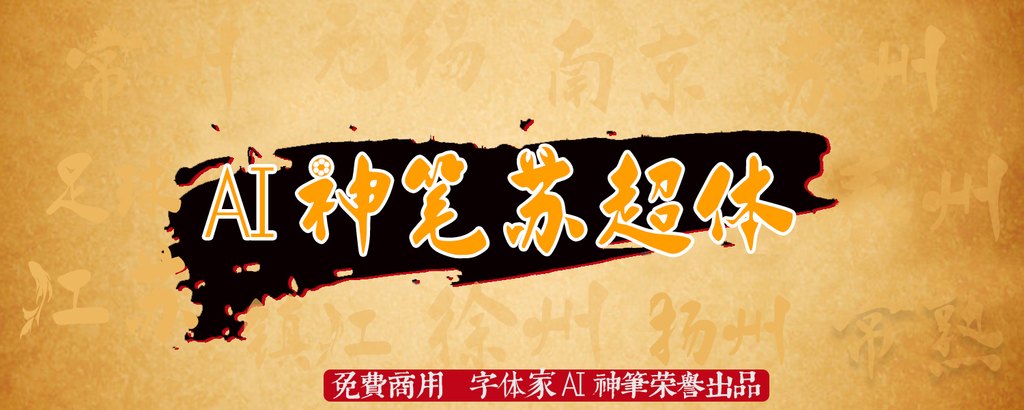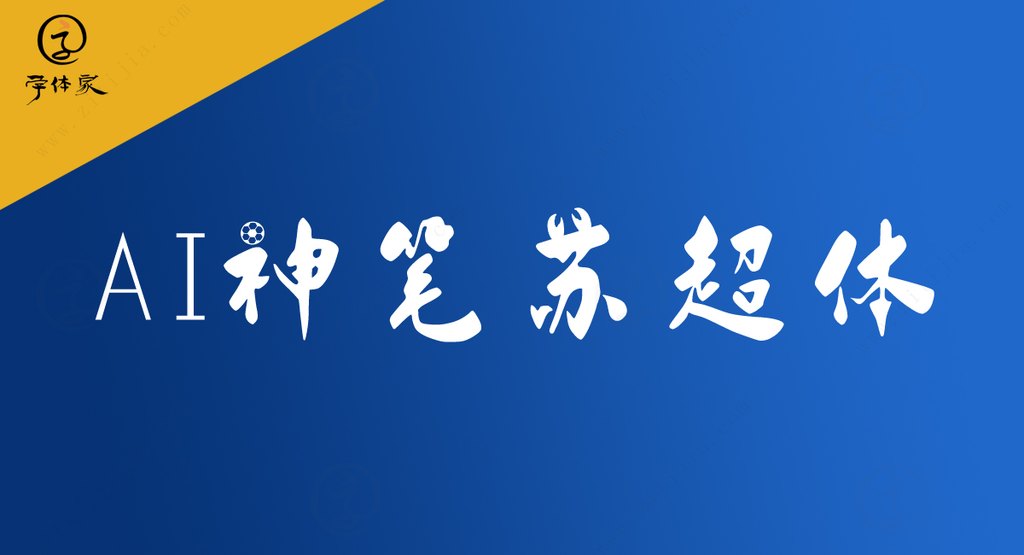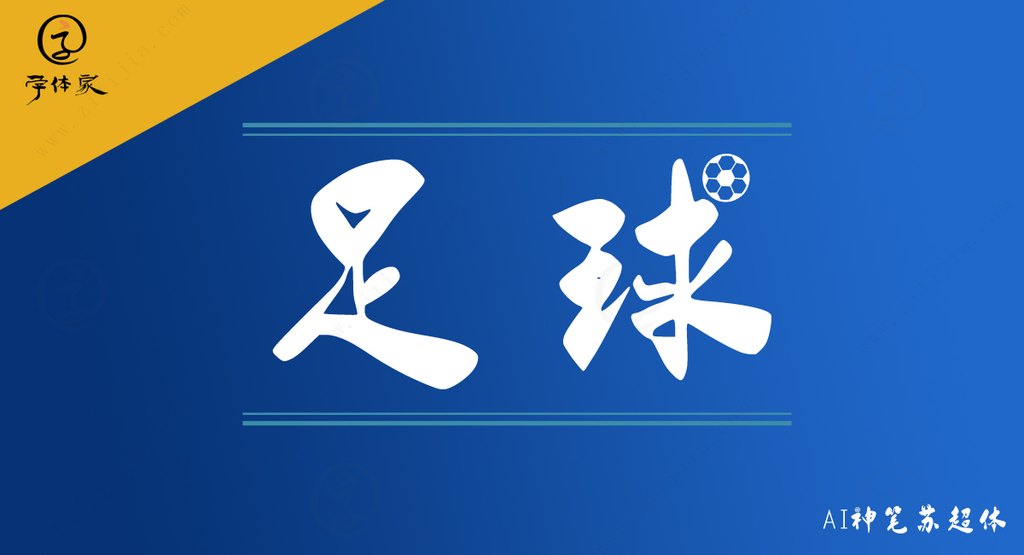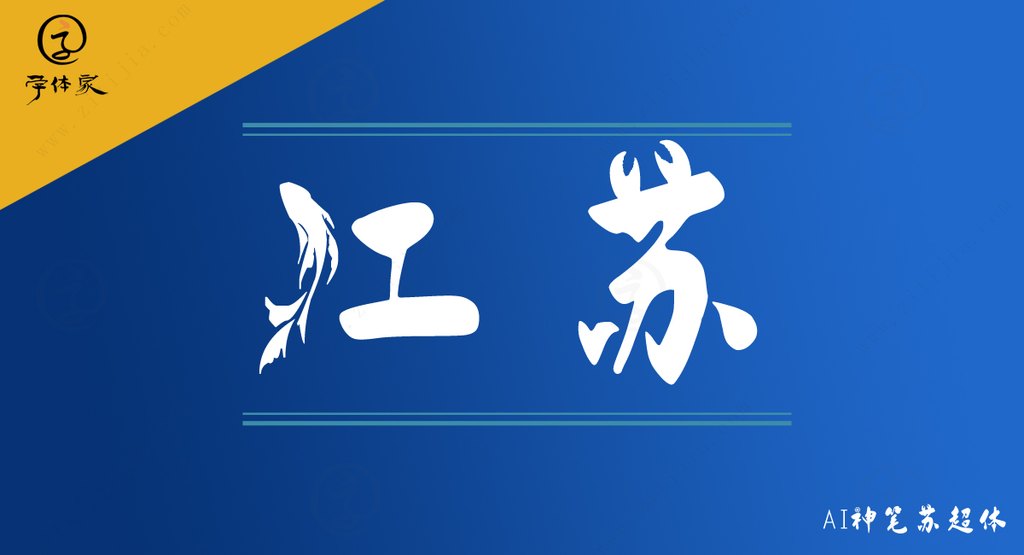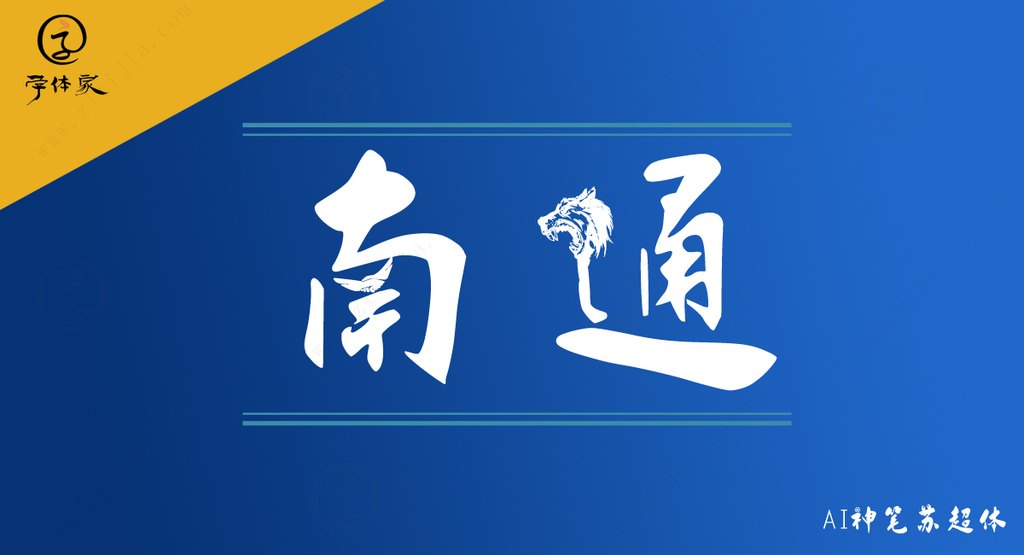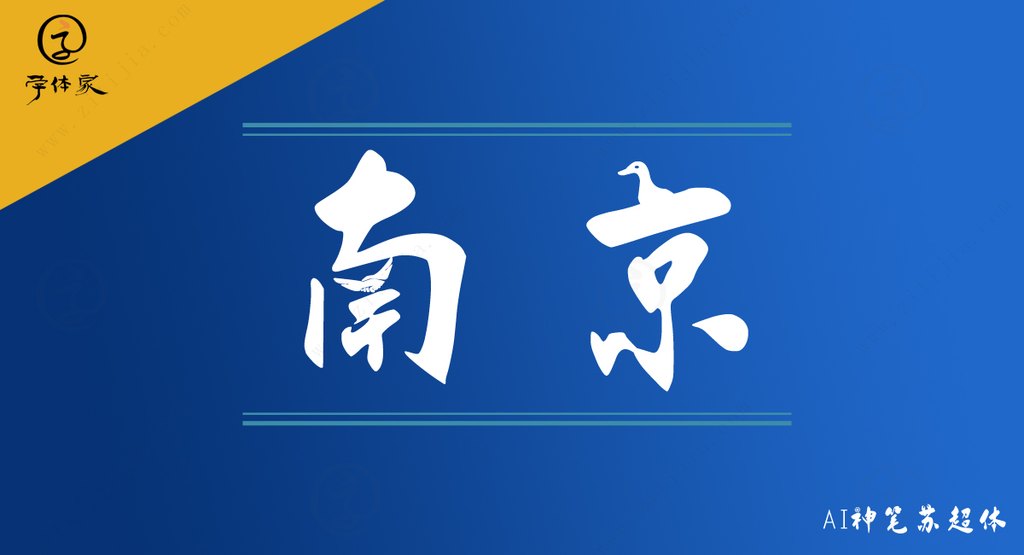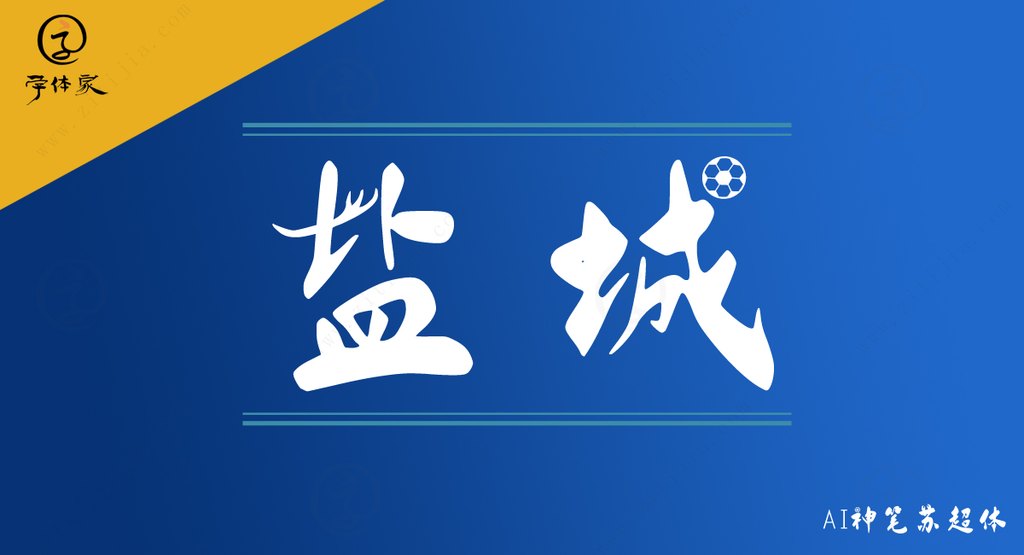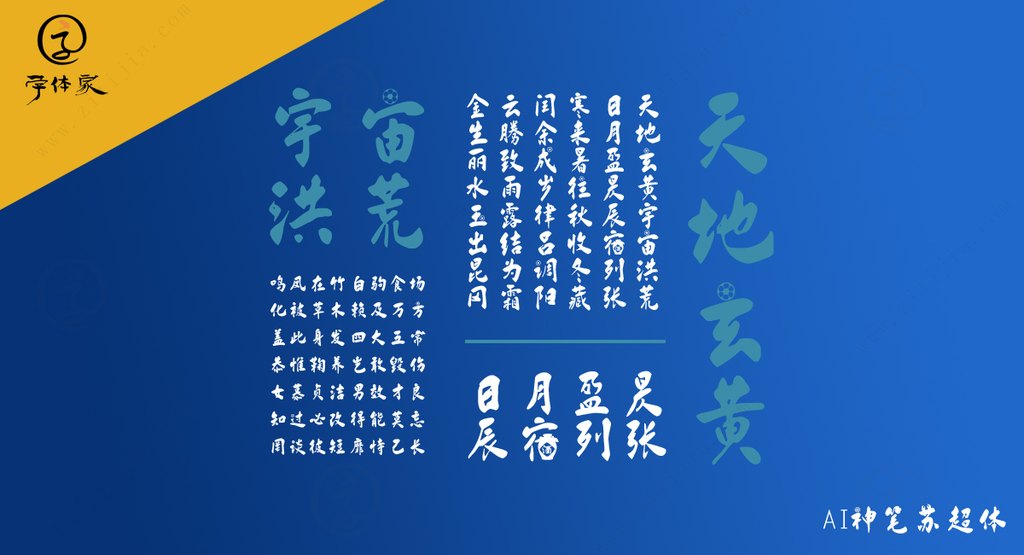
AI神笔苏超体免费商用字体问世啦
AI神笔苏超体是一款充满创意的艺术字体,巧妙地融合了传统毛笔书法的典雅与现代足球元素的活力。它诞生于“2025年江苏省城市足球联赛”为灵感的背景下,由字体家AI神笔造字团队精心打造。
灵动如行云流水
苏超体拥有毛笔书法风格,方正的骨架中藏着无限灵动。它展现出刚柔并济的特点,通过仿佛能触到的笔尖轻重提按,营造出气韵连贯的效果,如流水行舟般自然流畅。
跨越时空的设计
这款字体在传统的基础上加入了现代元素。设计师将足球的灵感融入其中,把“点”笔画改为足球的剪影,同时针对参赛城市名称的单字笔画进行了调整,融入了地方特色元素。这样的设计使字体既保留了古典风格,又不失时尚的现代感。
多元应用场景
拥有如此独特魅力的苏超体,适用于广泛的设计场景。无论是赛事宣传、纪念品设计,还是城市文化展示,这款字体都能助您一臂之力,带来耳目一新的品牌形象。
总的来说,AI神笔苏超体不仅仅是一款字体,它是一种艺术表达,将书法的优雅与足球的活力完美融合,成为古典与现代的桥梁。如果你需要一款同时兼具这两种特质的字体,苏超体将是不二之选。